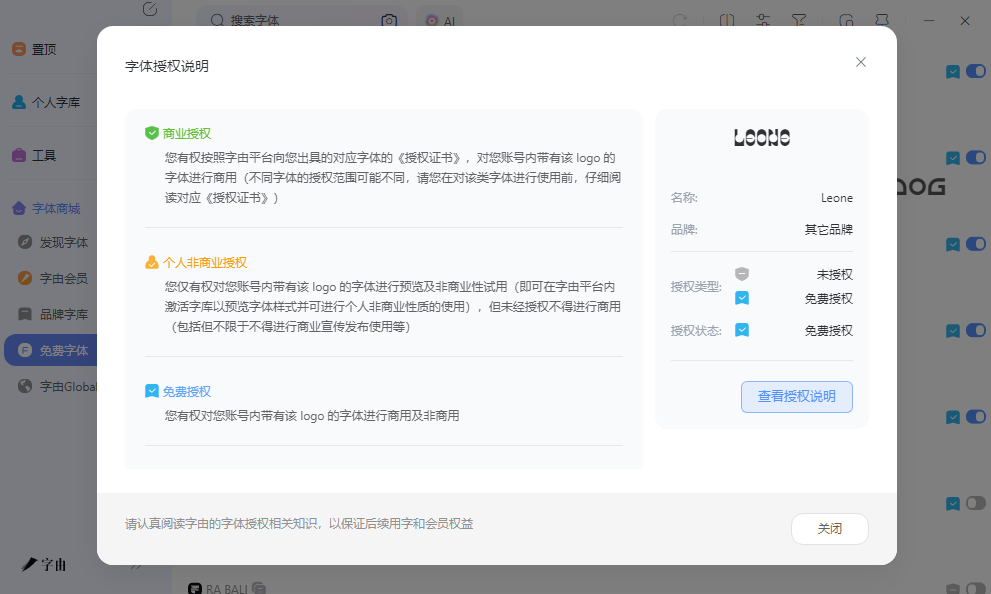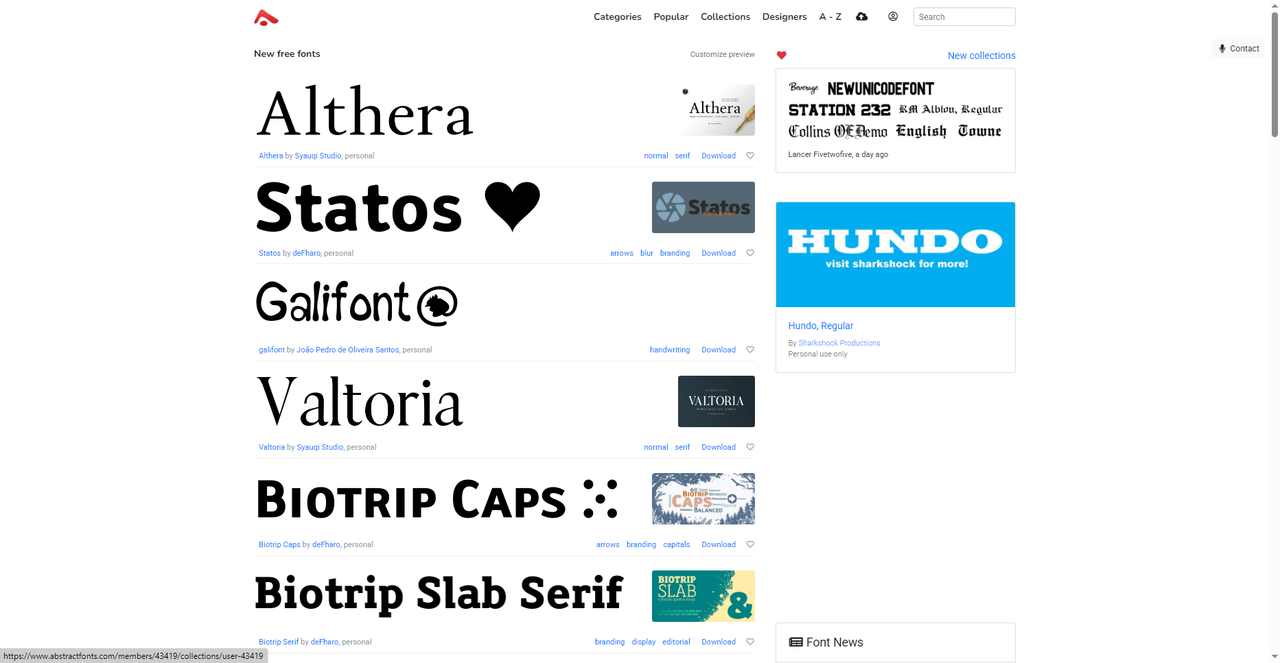
找字体文件时,很多人习惯去搜索引擎直接搜"某某字体下载",结果跳转到各种不明网站,下载的压缩包里除了字体文件还夹带着广告软件,甚至有些文件根本不是字体格式。真正靠谱的免费下载字体文件渠道,应该是授权清晰、文件干净、格式规范。这篇文章整理了五个平台,从中文管理到海外独立字体都有覆盖,帮助你在获取字体文件时避开各种坑。
传统模式是去不同网站下载安装包,解压后手动安装到系统,字体文件散落在各处,时间久了来源和授权都记不清。字由的做法是把获取和管理整理到一个客户端里,浏览到合适的字体后直接激活使用,不需要接触底层的安装文件。这种方式既省去了下载解压的麻烦,也避免了安装来源不明的文件带来的安全风险。
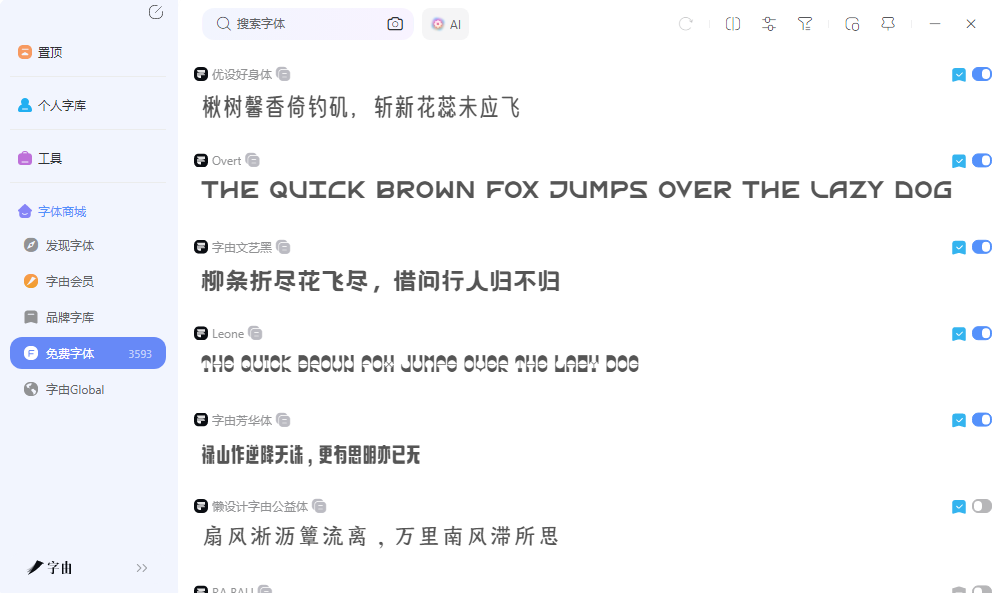
字体库里的资源来自正规厂商,授权信息在卡片上直接可见。对于需要免费下载字体文件后续自由使用的用户来说,字由也支持导出字体文件。激活后的字体可以通过客户端管理,本地已有的字体文件也能导入到个人云字库中统一归档。导入流程简单,拖拽上传后系统自动识别格式,支持TTF和OTF两种主流格式。导入后可以给字体打标签、建分组,和平台上的字体一起管理,相当于给散落在硬盘各处的字体文件建了一个统一的数字档案。找的时候不需要再翻硬盘,直接在客户端里搜索就能定位到。
2、Abstract Fonts
Abstract Fonts是截图中展示的平台,首页列出了Althera、Statos、Galifont、Valtoria、Biotrip Caps、Biotrip Slab Serif等多款字体。每款字体都标注了作者名称,比如Althera由Syaqil Studio设计,Statos由deFharo设计,右侧有风格标签和Download按钮。这种展示方式比较直观,字体以大图形式呈现,一目了然。
作为免费下载字体文件的来源,这里的字体风格偏向个性化,很多来自独立设计师,适合想找一些有辨识度、不太会跟别人撞款的字体的用户。
3、Fontsly
Fontsly是一个大型免费字体站,资源量比较大,风格覆盖从基础无衬线体到装饰性强的展示字体。网站上的字体很多标注了免费下载,但授权类型不完全统一,有些仅限个人使用,有些允许商用,下载前需要查看详情页的授权说明。平台是用户上传为主,字体质量参差不齐,有些字体字符集不完整,有些则带有广告捆绑,下载后建议先用字体查看器确认文件是否干净。
分类体系比较直观,可以按风格标签逐步筛选。每款字体都配有预览图,预览框支持输入自己的文案查看效果。Fontsly作为免费下载字体文件的渠道,其优势在于资源量大、更新频繁。
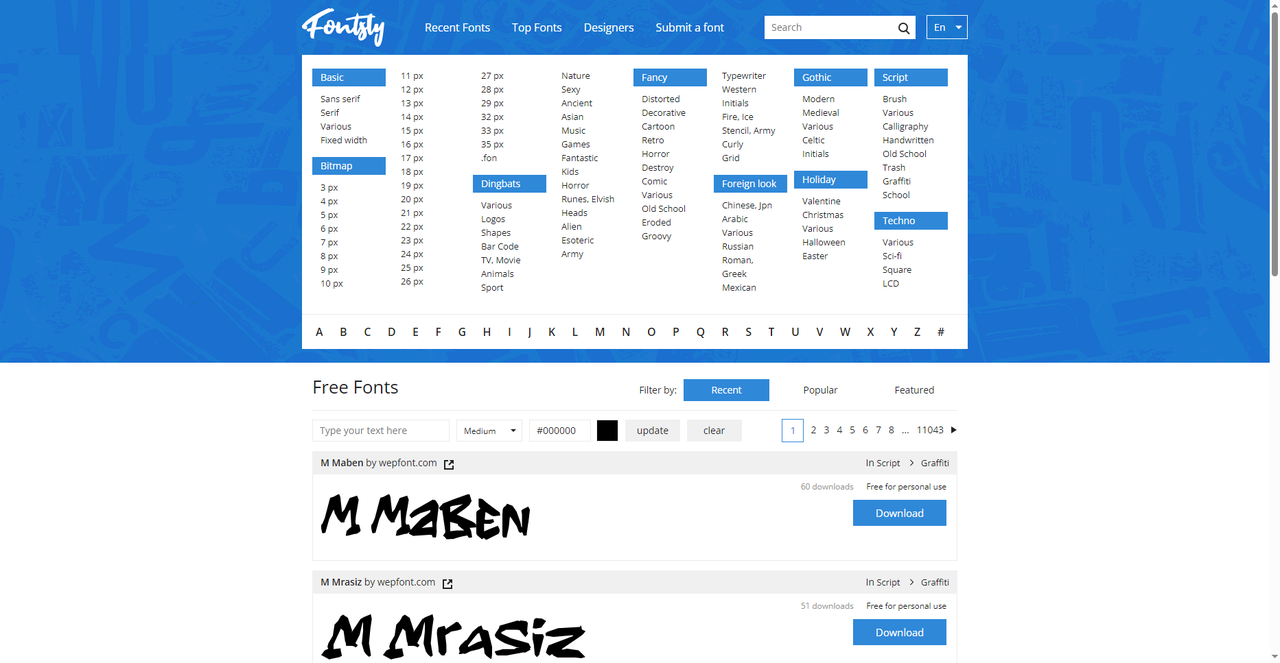
4、freefont
这是一个德文免费字体站,主要面向德语用户,但也收录了不少支持拉丁字母的字体资源。网站上的字体按风格做了分类,预览图清晰,下载按钮直接获取字体文件,流程顺畅。因为主要服务德语市场,平台上有些字体带有德文特色的字符设计,比如特殊的变音符号,处理德语区项目时比较实用。
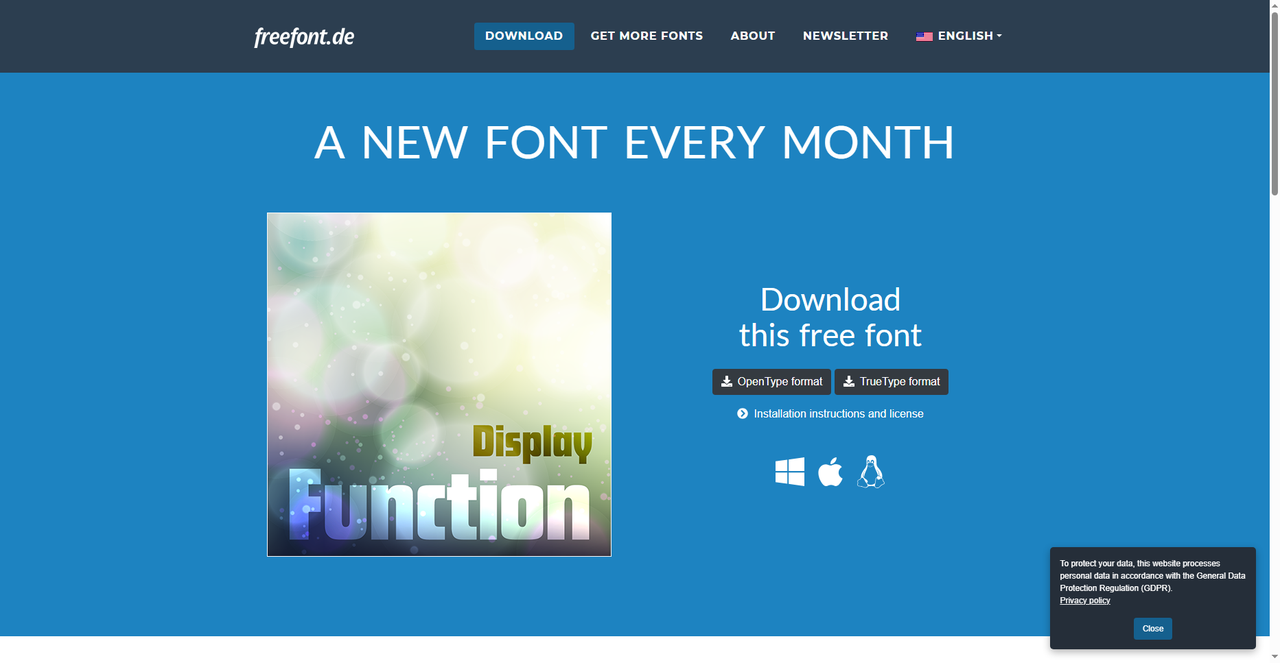
5、Lost Type
Lost Type是一个独立字体厂牌,和前面几个资源聚合型平台不同,这里的字体全部由团队自己设计或与合作设计师共同开发。字体风格偏向实验性和艺术化,很多设计带有独特的视觉个性,在常规渠道不太容易找到。平台上大部分字体是付费的,但会提供试用版本或者部分字重的免费下载,格式为标准的TTF和OTF,文件干净无捆绑。
对于追求字体独特性、愿意为好设计付费的用户来说,Lost Type的品质在独立字体领域属于较高水准。试用版本虽然字符集有限,但足以判断一款字体的视觉风格是否适合自己的项目,体验后再决定是否购买完整版,这种方式比盲目下载更有针对性。作为免费下载字体文件的渠道,Lost Type的价值在于提供了一个低门槛的体验入口,让设计师在购买前先确认品质。